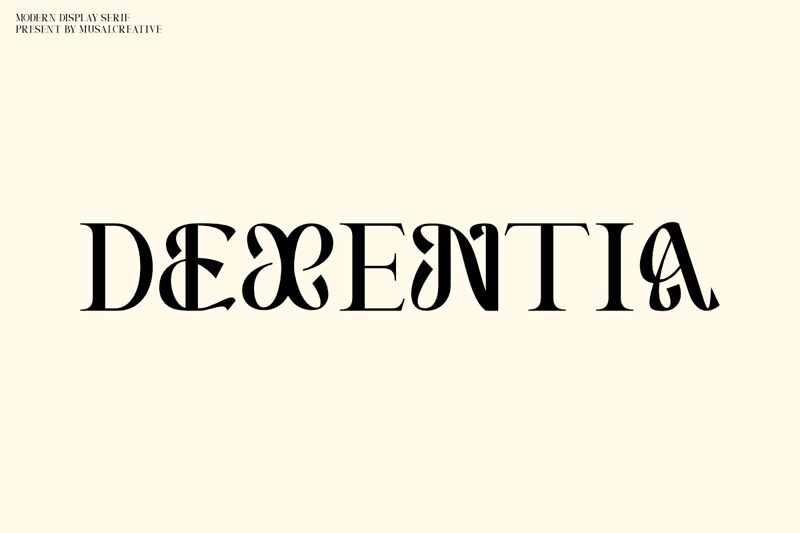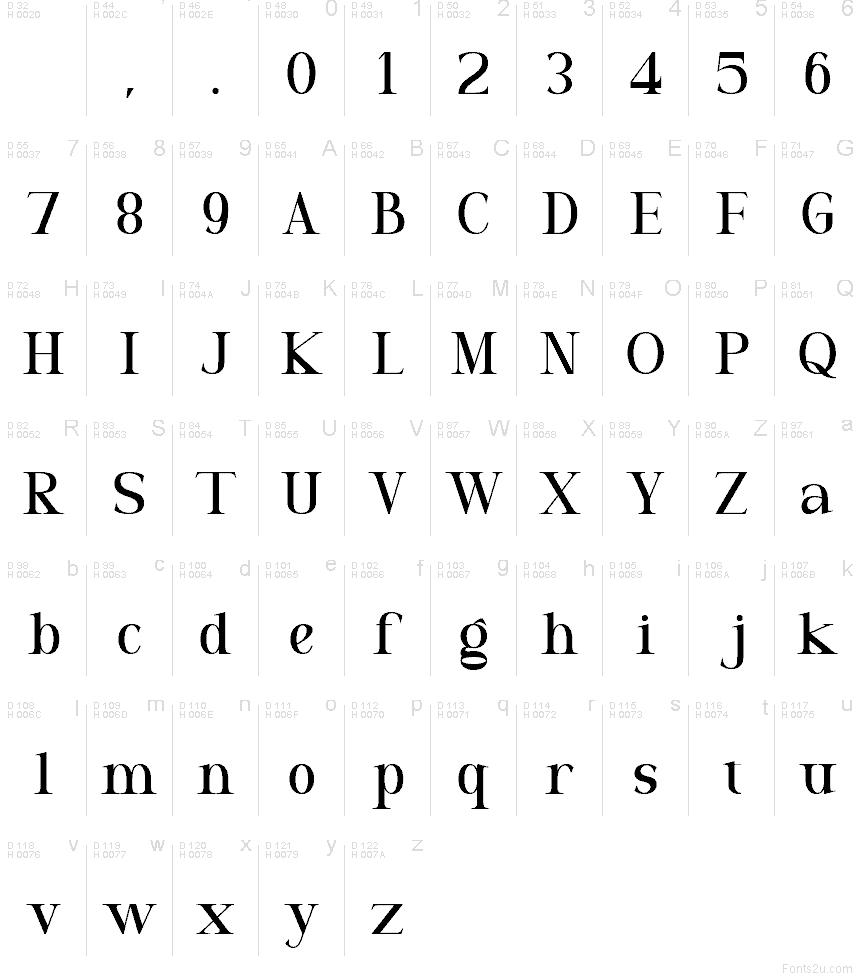
Dexentia Regular
Dexentia, bezplatné patkové písmo s vysokým kontrastom od Muksal Creative, vytvára čistý rytmus vďaka zaobleným krivkám a jemným spojom, čo písmu dodáva vycibrený a elegantný charakter. Napätie medzi úzkymi vlasovými líniami a plnšími zaoblenými ťahmi pôsobí veľmi rafinovane, zatiaľ čo ostrejšie tvary dodávajú písmu módny šmrnc, ktorý ho odlišuje od bežného knižného písma.
Táto kombinácia sa skvele hodí na titulky časopisov, obaly kozmetiky, branding butikov, pozvánky či prémiovú grafiku na sociálne siete. Najmä krátke nadpisy ťažia z kontrastnej textúry, ktorá dodáva slovám potrebnú eleganciu v redakčných materiáloch či na etiketách produktov bez potreby ďalších ozdôb.